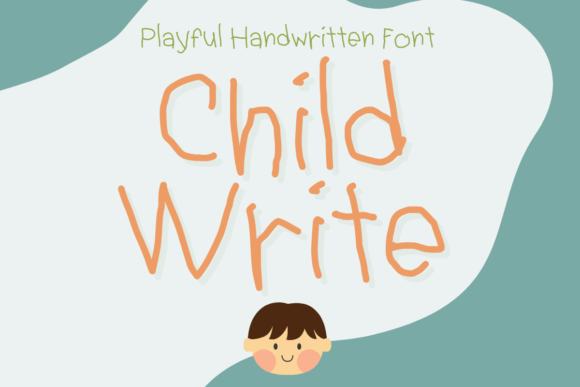
Child Write
Child Write : La police qui redonne le sourire à vos créations
Vous cherchez une police à la fois ludique, adorable et ultra‑versatile ? Child Write est la réponse à toutes vos attentes. Inspirée d’une écriture manuscrite d’enfant, elle apporte une touche d’innocence et de créativité à chaque projet digital.
Pourquoi choisir Child Write pour vos projets ?
- Style unique et charmant : chaque glyphe ressemble à une petite note griffonnée à la main, parfaite pour créer une ambiance chaleureuse.
- Excellente lisibilité : malgré son aspect « dessiné », la police reste claire même à petite taille, ce qui la rend idéale pour les textes d’accompagnement.
- Adaptabilité : que vous réalisez un logo, une invitation, un planner digital ou un album photo, Child Write s’intègre naturellement.
Idées d’utilisation concrètes
- Création de logos pour marques orientées enfance ou produits créatifs.
- Design de planners numériques et d’agendas interactifs.
- Réalisation d’invitations de fête, cartes de vœux et papeterie personnalisée.
- Illustration d’articles de blog et de newsletters pour capter l’attention dès le premier regard.
- Montage d’albums photo numériques avec des légendes qui ressemblent à des souvenirs écrits à la main.
- Conception d’illustrations Procreate où chaque texte devient une partie du dessin.
Conclusion : la touche enfantine qui booste votre visibilité